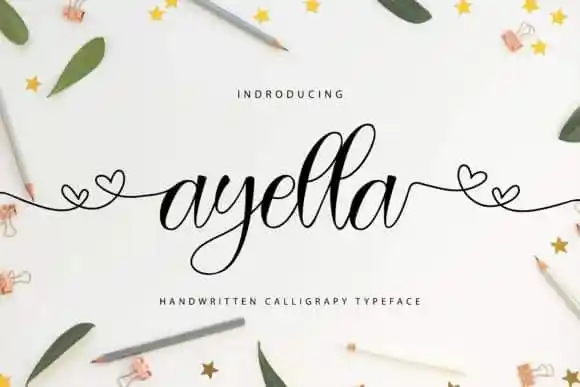
Ayella Calligraphy Font
A Ayella Calligraphy Font é uma escolha perfeita para aqueles que buscam um estilo elegante e casual ao mesmo tempo. Feita pelo designer Letterfand Studio, esta fonte vem com várias alternativas para criar um toque único de personalização. Com swashes, alterna estilísticas, alternativas, formas iniciais e terminais, você pode transformar seu texto em uma obra de arte que transmite conforto e simplicidade sem deixar de lado a autenticidade de sua escrita. Perfeita para criar cartões de aniversário adoráveis, invitations casamentares únicas ou artesanato de estação de trabalho incrivelmente bonito, esta fonte oferece uma maneira divertida e criativa de personalizar suas mensagens digitais no Facebook, Instagram ou outros canais sociais. Com sua aparência cuidadosamente construída para transmitir um sentimento de amizade e descontração, a Ayella Calligraphy Font é um excelente recurso para designers gráficos que buscam adicionar uma pitada de criatividade a seus projetos.